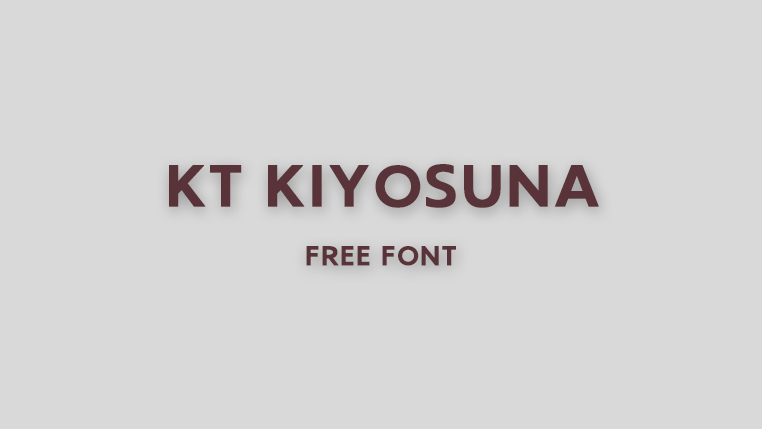
想要一款字重不多、但气质安静现代的无衬线体?日本设计师出手的 KT Kiyosuna Sans,低对比度的几何字形,读起来非常舒服。
字体介绍
KT Kiyosuna Sans 由日本设计师 Reiya WATANABE 设计,是一款采用 SIL Open Font License 1.1 开源协议发布的几何风格无衬线字体,个人和商业项目都可以免费使用,授权非常友好。它的字形采用低对比度处理,笔画粗细变化很小,整体气质温和而现代,既不会抢走内容的风头,又能让版面显得干净利落,是那种越用越顺手的类型。
字体细节里藏着巧思:字母 i 的点以及部分标点被处理成菱形,让简洁的几何造型多了一点识别度。官方开源授权让它在电子书、杂志、软件界面等场景里都可以放心落地,同时它的日文、拉丁、西里尔等多语言覆盖也适合国际化项目,是实用型日系字体的好选择,上手成本几乎为零,非常适合长期使用。
字形特点
几何现代:以几何造型为基础的现代无衬线体,线条简洁干净,整体气质温和不张扬,既适合标题也适合正文,排版耐看且不过时,通用性很强。
低对比度:笔画粗细变化很小,字形稳定均匀,长时间阅读也不容易疲劳,无论是电子屏幕还是印刷正文都能胜任,阅读体验平稳舒适。
菱形细节:字母 i 的点以及部分标点采用菱形处理,在简洁的造型中埋下精致的记忆点,让整套字多了一点灵动的识别度,细节控会很喜欢。
多语言支持:覆盖日文、拉丁字母与西里尔文,还包含中文数字、罗马数字、上下标等实用符号,跨语言项目使用范围更广,符号细节也考虑周到。
字重与字数
共 2 个字重:Light 与 Bold,另有斜体等配套可结合使用,适合标题与正文的常见搭配需求,覆盖日常排版足够。
含日文字符集、拉丁字母、西里尔文,并包含中文数字、等宽数字、罗马数字、上下标、分子分母、带圆圈数字等符号;不含完整中文字符集,中文排版需另行搭配。
字体使用建议
这款字体在以下场景表现尤其出色:
- 电子书与杂志等阅读类产品
- 国际化品牌与全球官网
- 软件界面与应用内标题正文
- 科技、教育、儿童类现代生活品牌